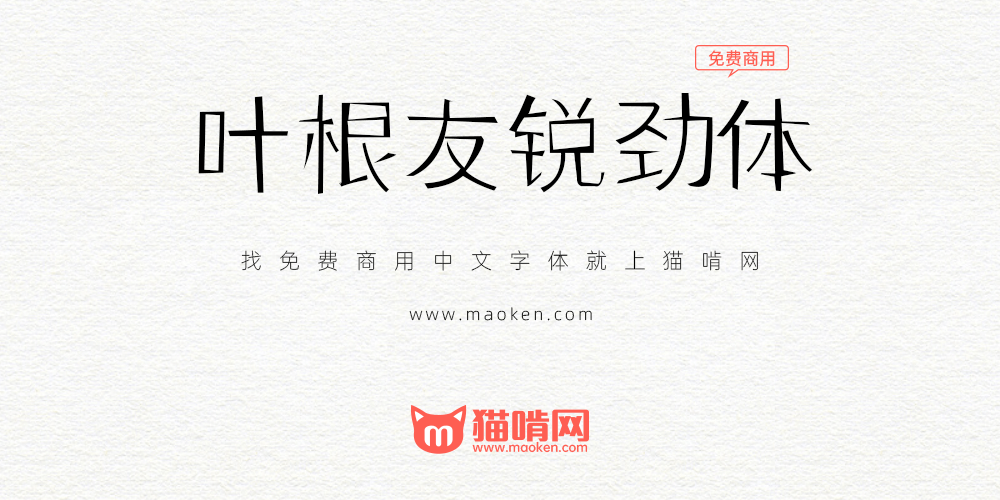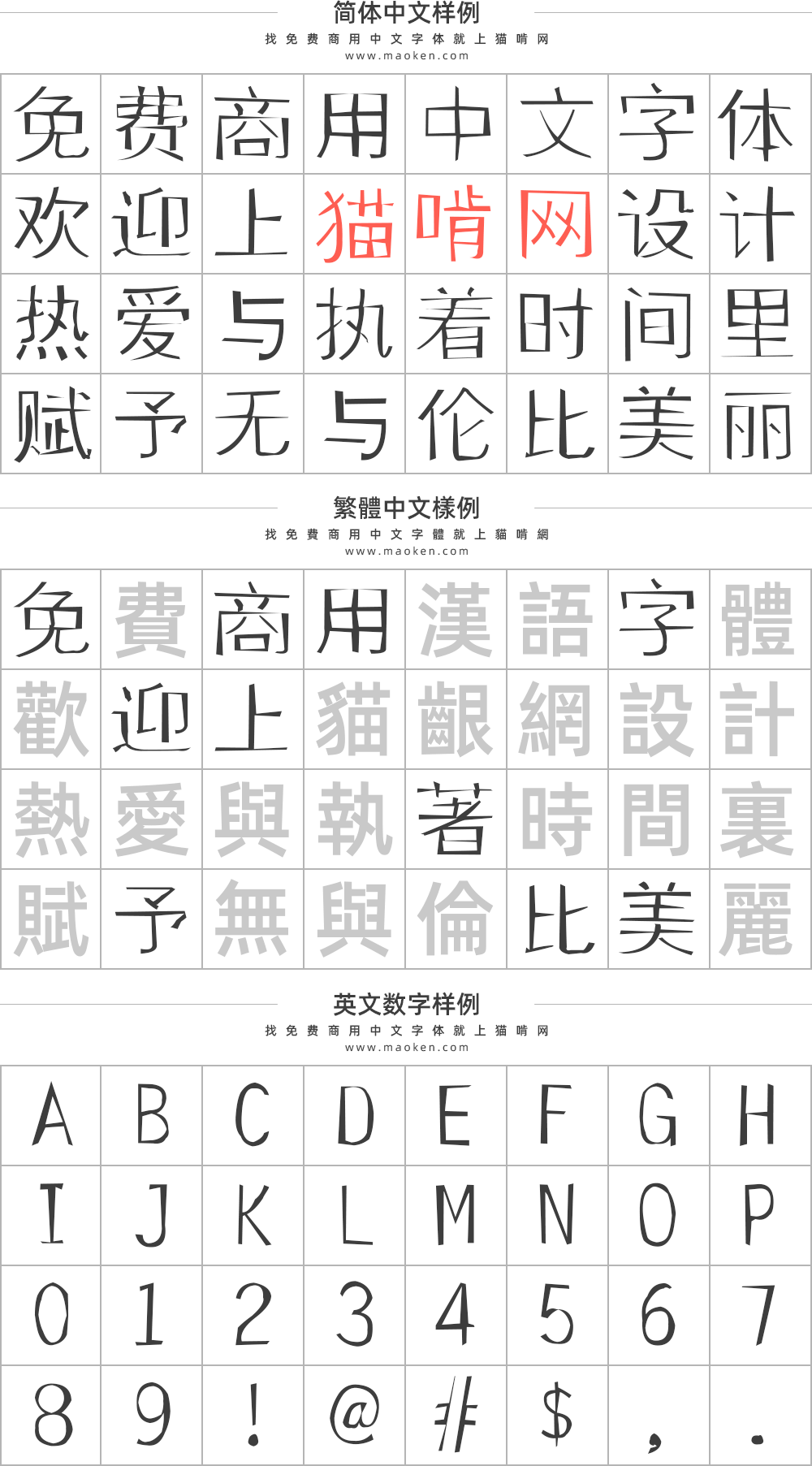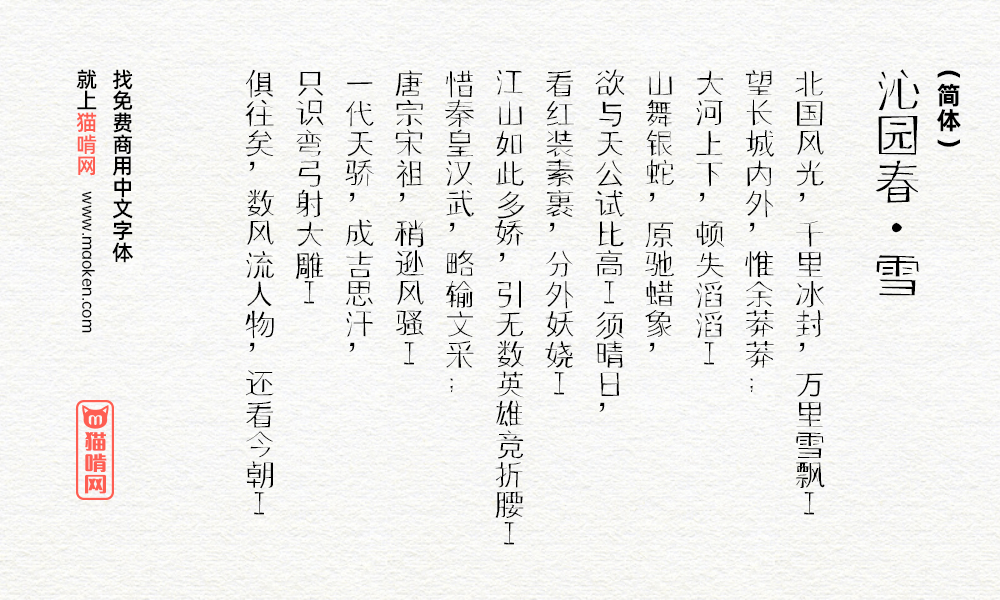
叶根友锐劲体:极具特色的坚韧有力细线字型
字体作者:叶根友 (中国大陆) 字体字重:1个
字体名称:叶根友锐劲体PS中字体名称:叶根友锐劲体
字体版本:Version 1.00 收录汉字:简体★★★★★ / 繁体★
叶根友锐劲体是由书法家叶根友先生设计的一款字体,该字体整体风格大气,坚韧有力,结构合理,字库完整,是一款非常有特色的字体。适合平面设计,艺术设计等载体应用。